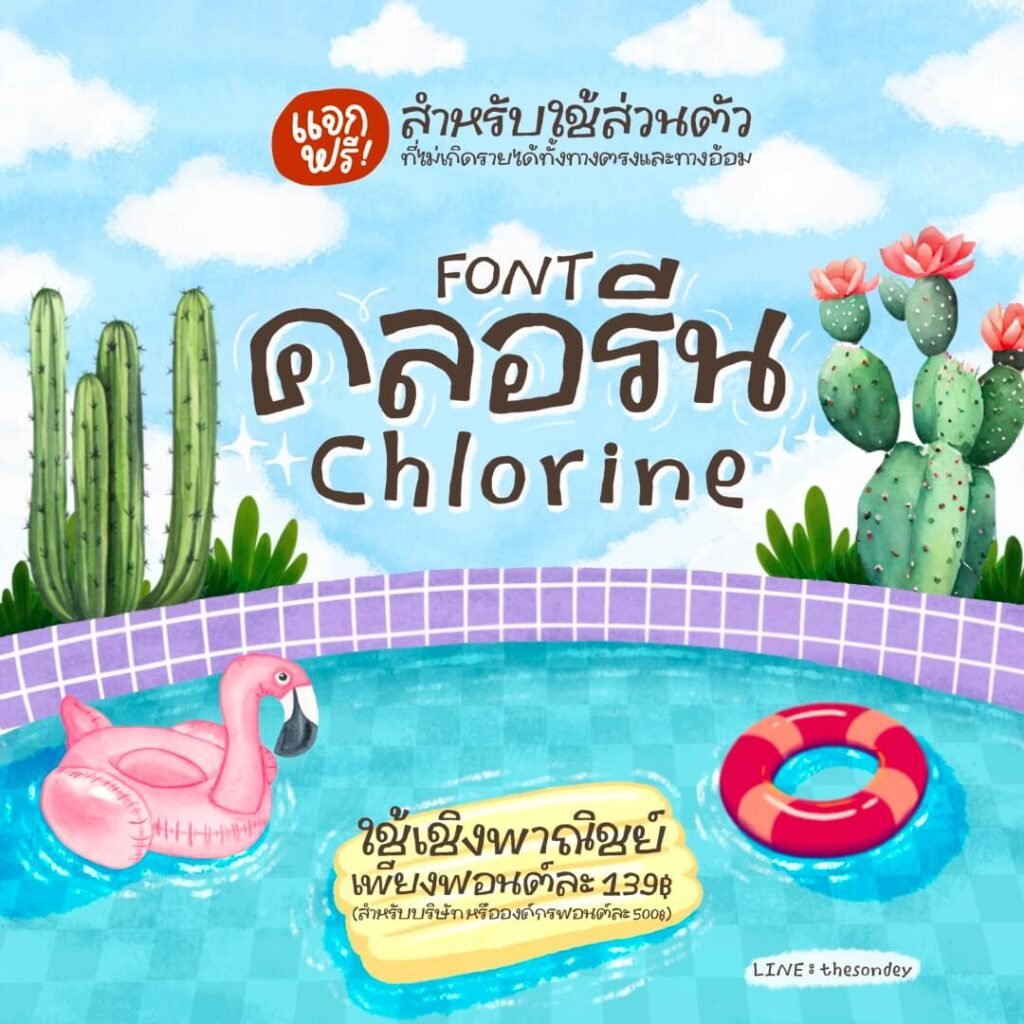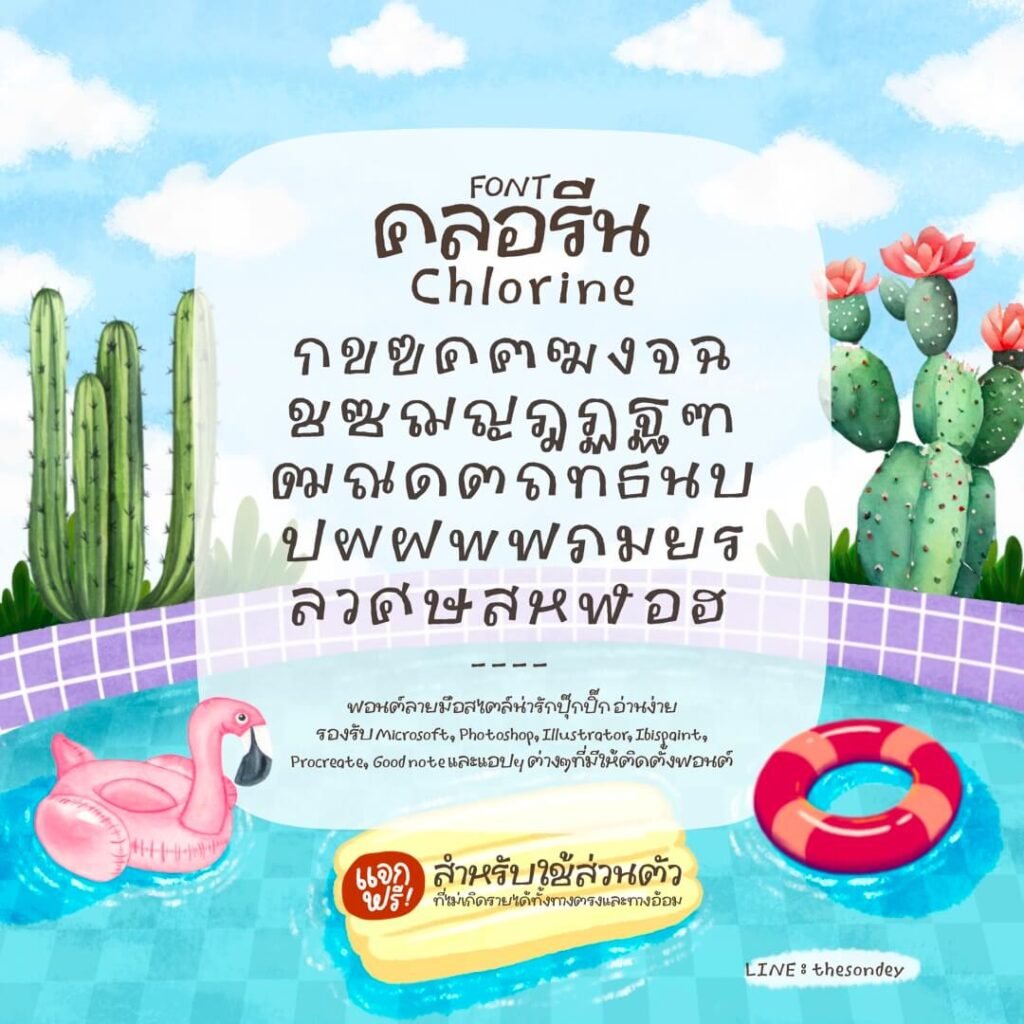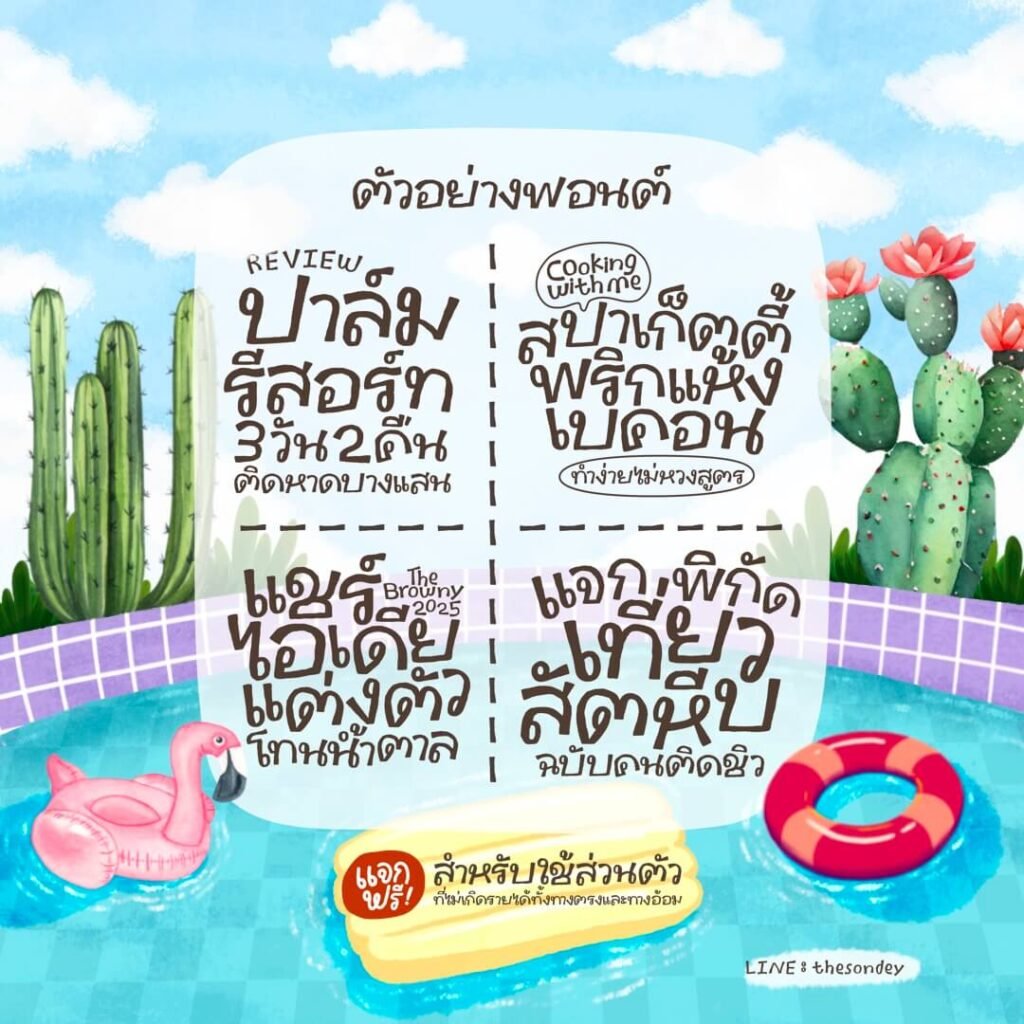
คลอรีน (PG Chlorine)
ฟอนต์ลายมือสไตล์น่ารักปุ๊กปิ๊ก อ่านง่าย รองรับ Microsoft, Photoshop, Illustrator, CapCut, ibisPaint, Procreate, Good Note และแอปฯ ต่างๆ ที่มีให้ติดตั้งฟอนต์